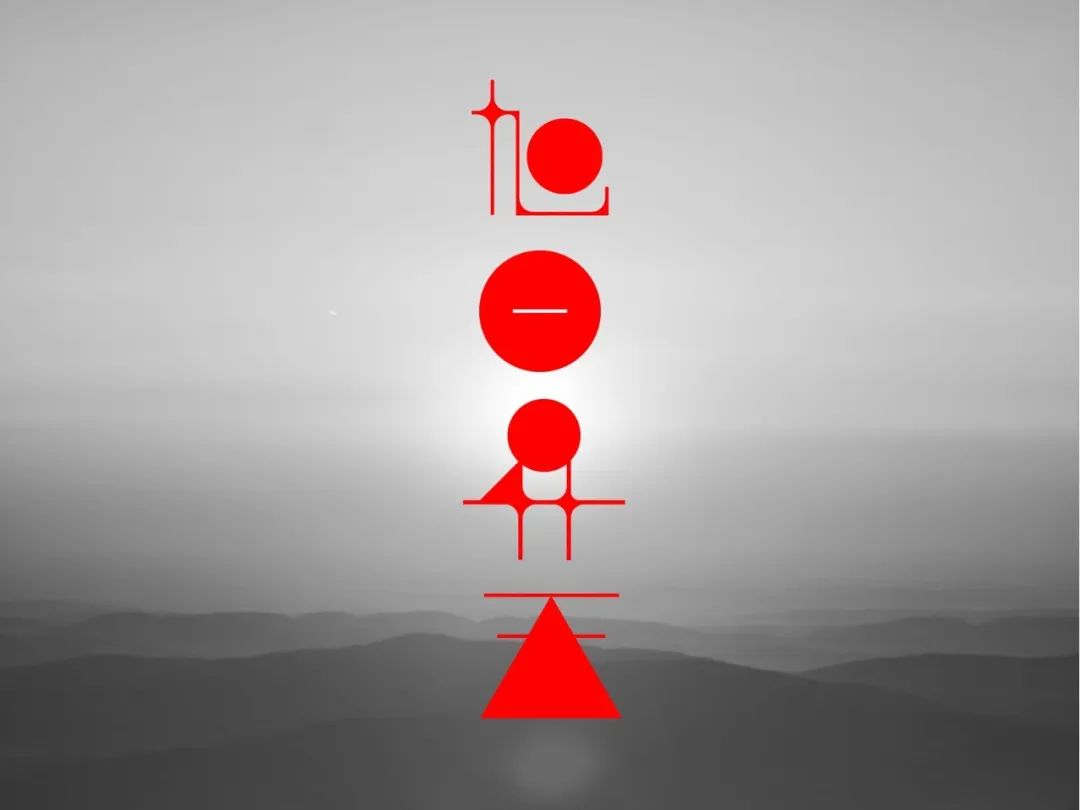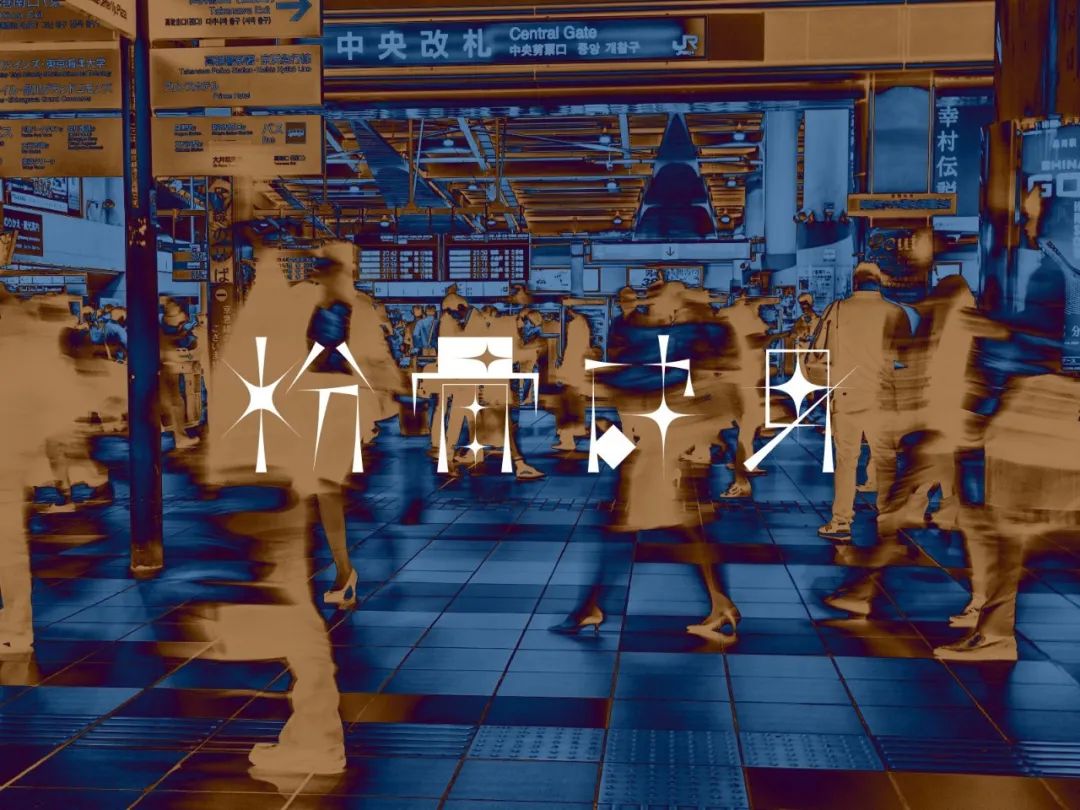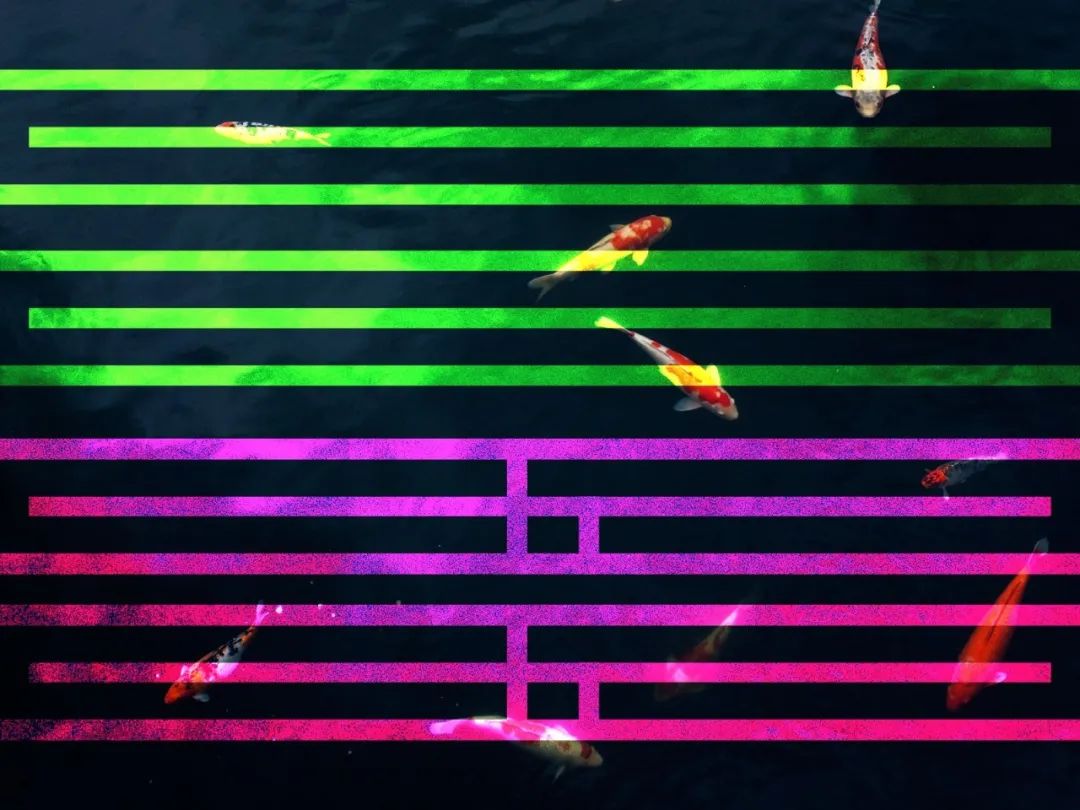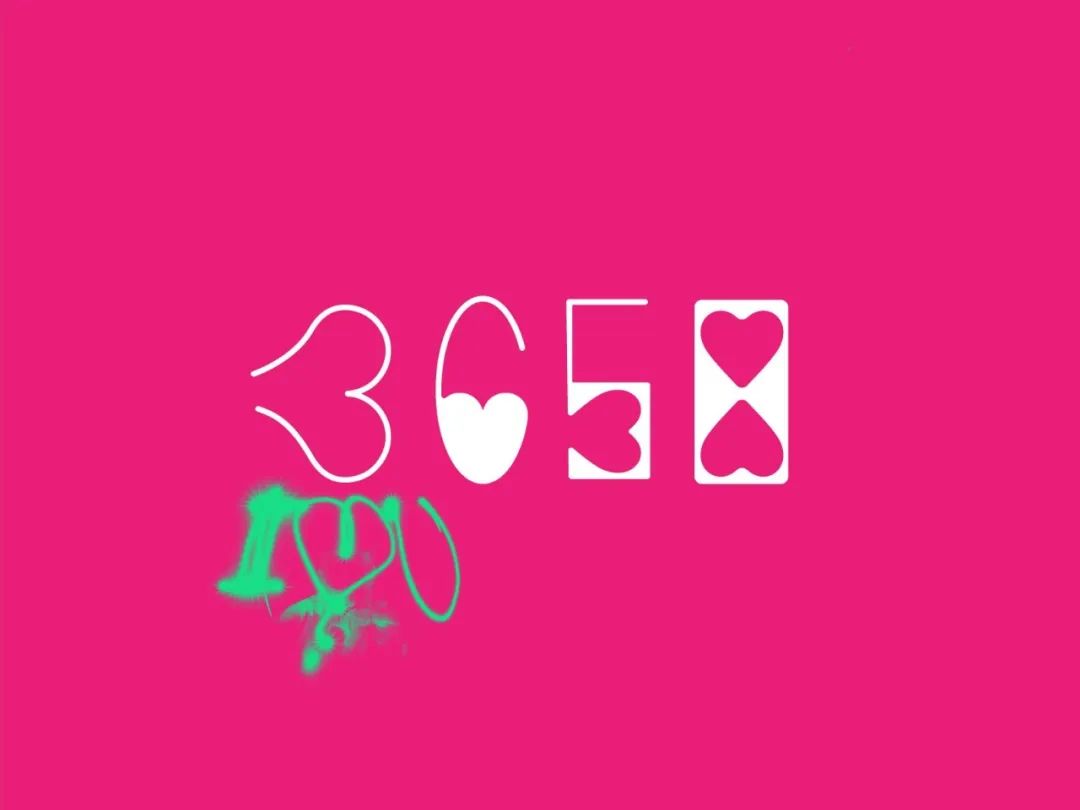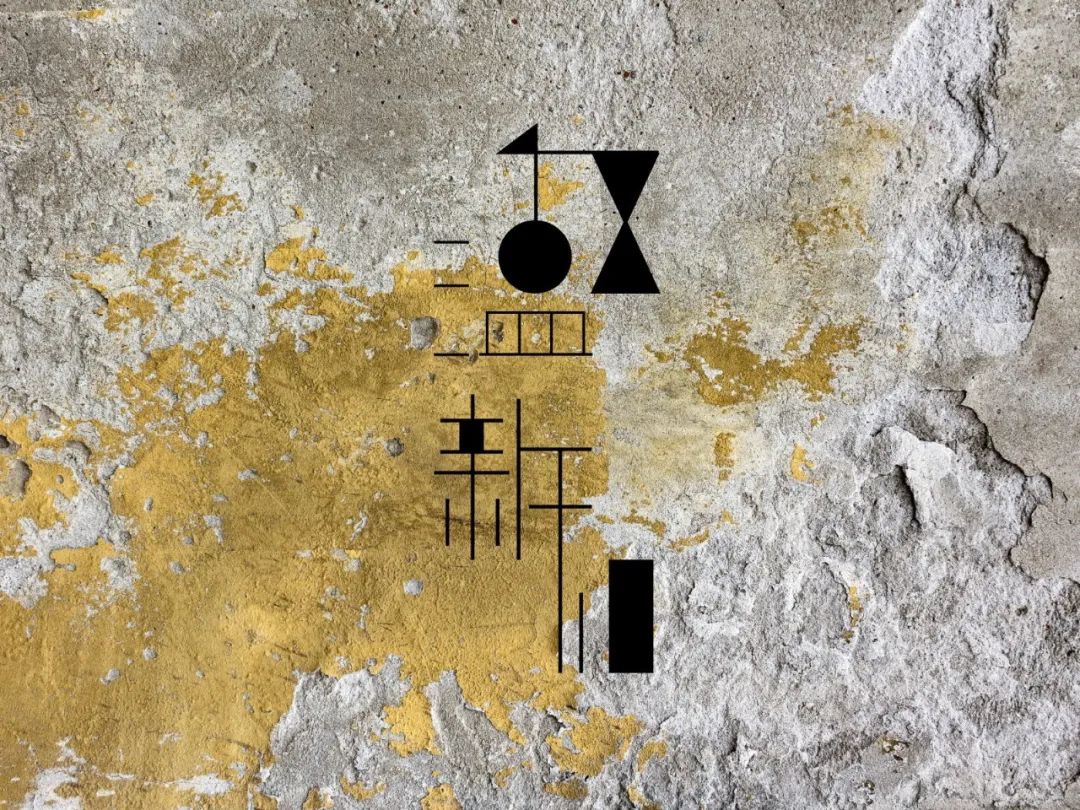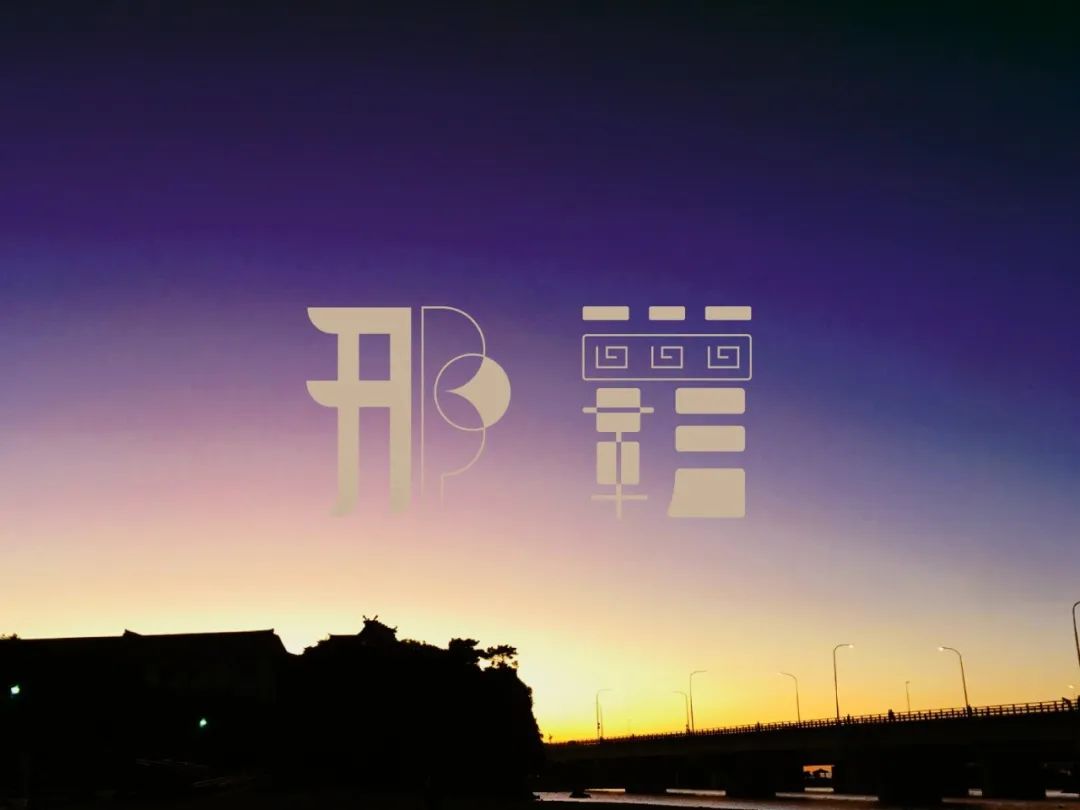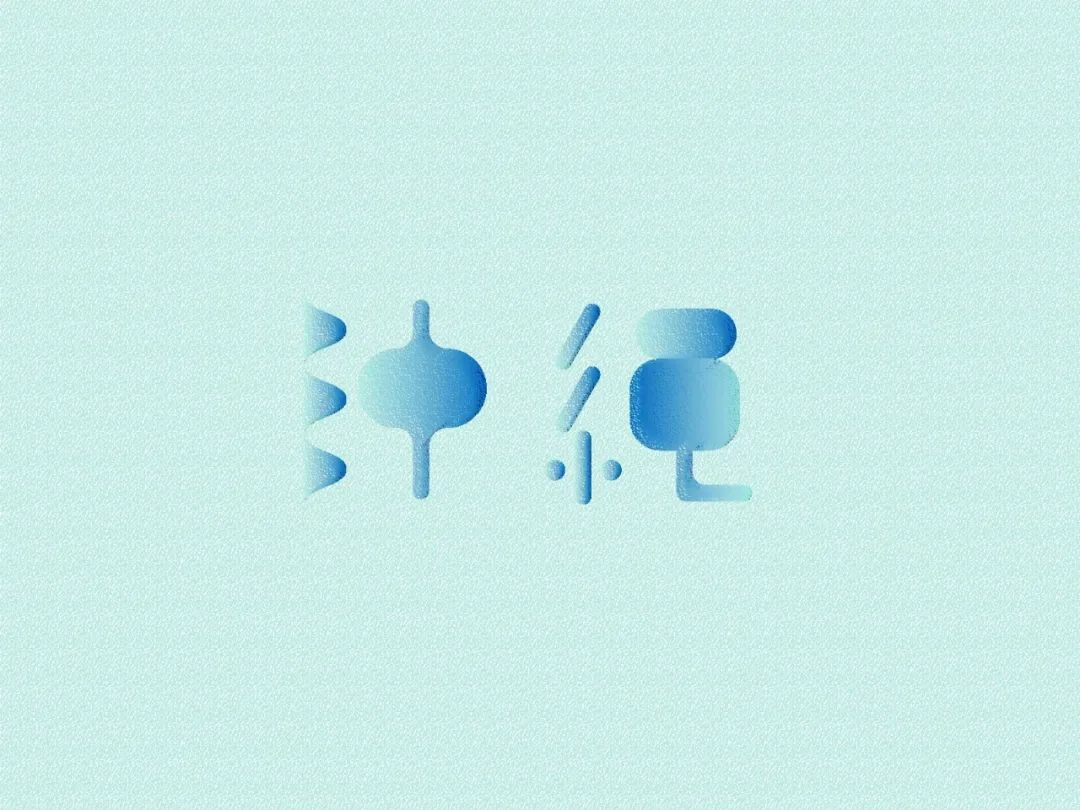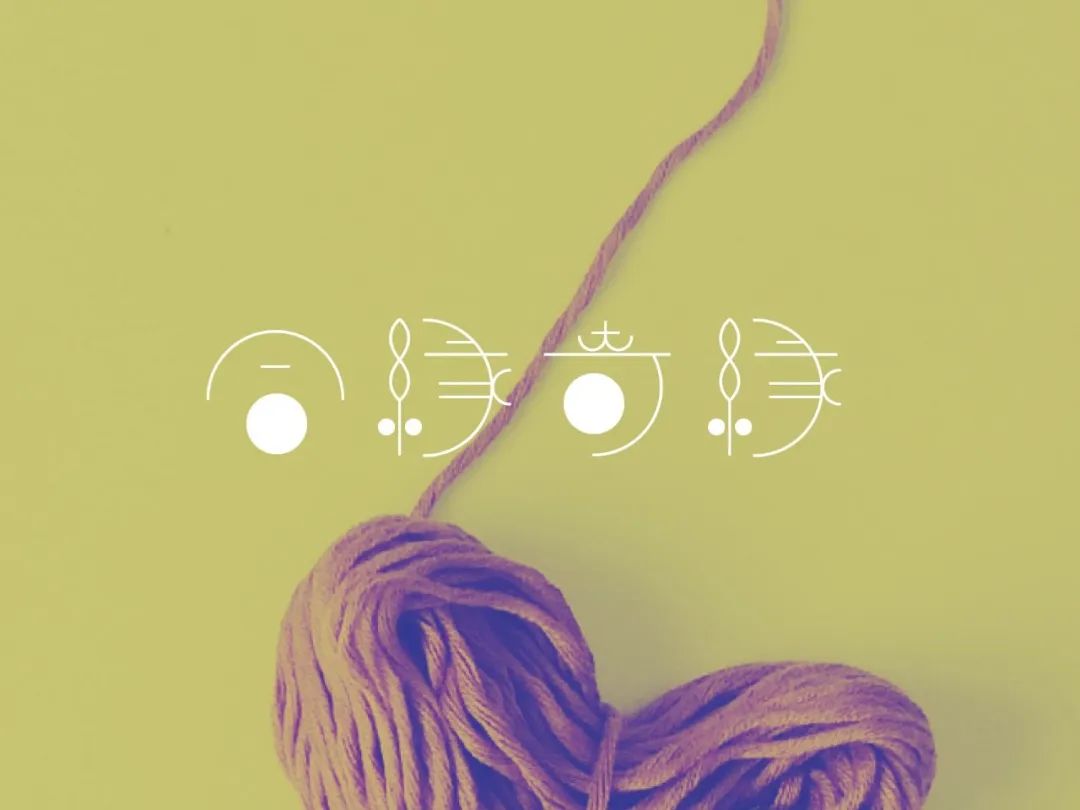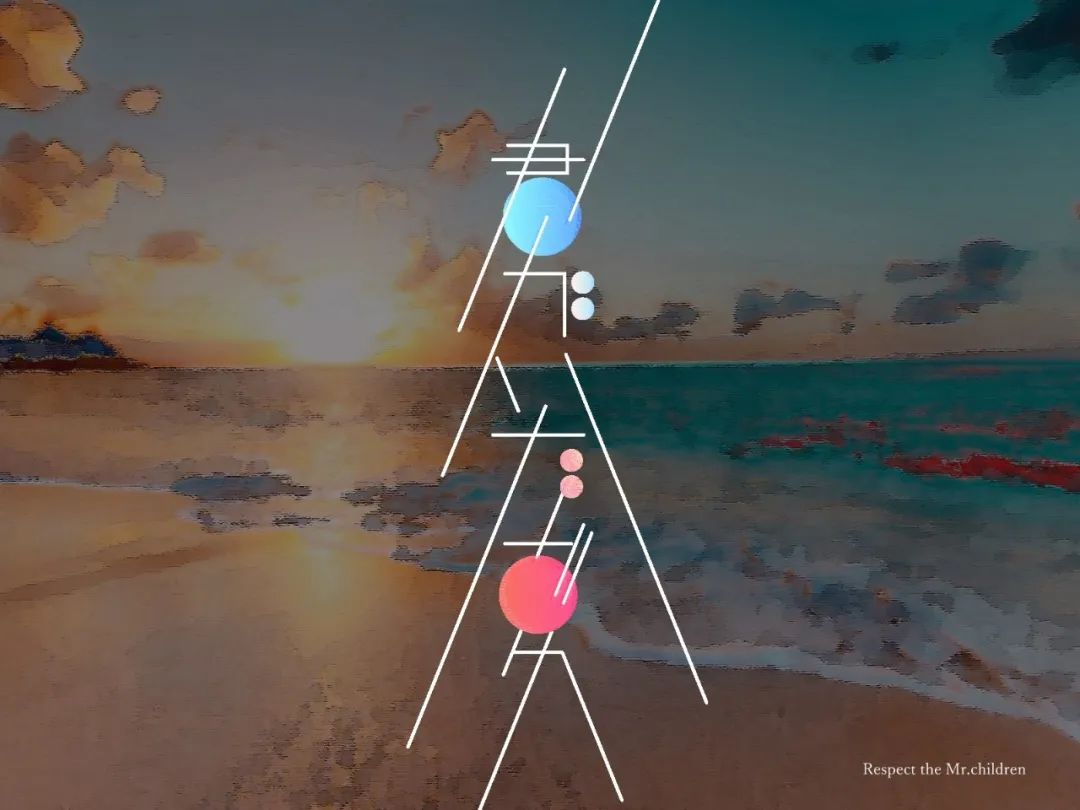
60张创意字体设计分享,带你感受冲出屏幕的生命力!
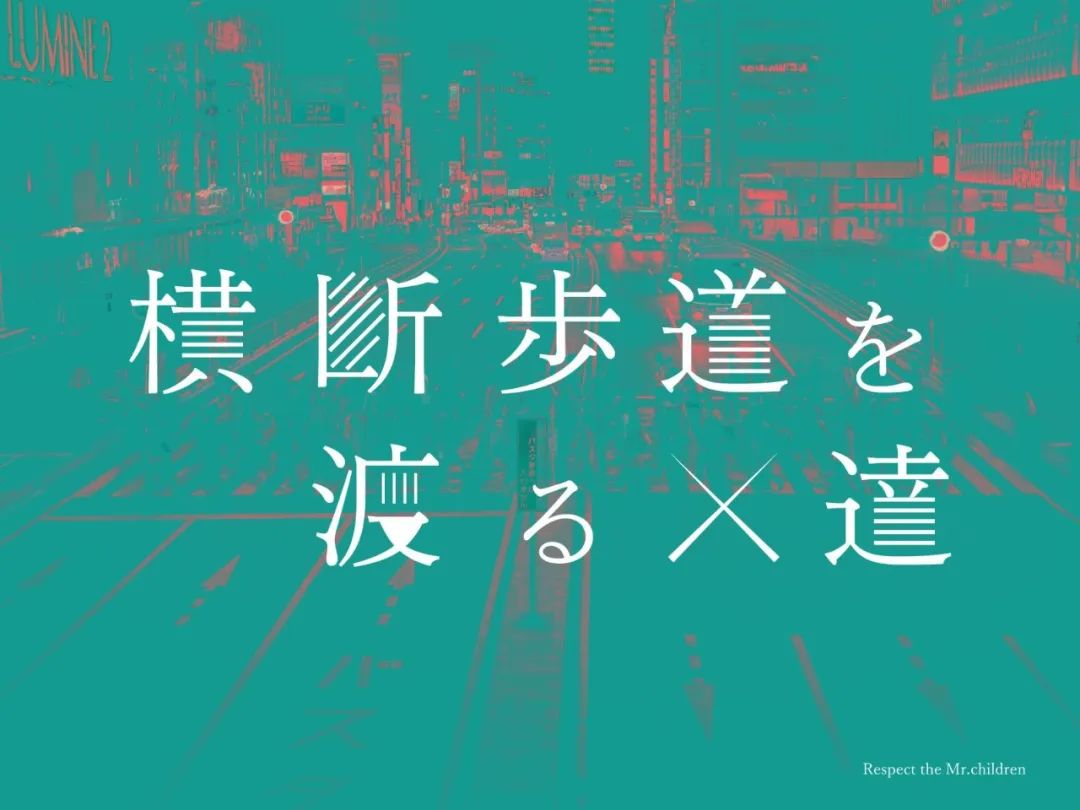
今天跟大家分享一位来自东京的平面设计师Mitsuru Terasaki 。他将文字与图形结合在一起,充满了生命力和感染力,看了他的作品,你还愁没灵感吗?
01
Mr.children 横断歩道を渡る人達
02
旭日昇天
03
粉骨砕身
04
三三五五
05
Mr.children 365日
06
温故知新
07
那覇(NAHA)
08
沖縄(OKINAWA)
09
合縁奇縁
10
Mr.children 君がいた夏
11
行雲流水
12
輪廻転生
13
海千山千
14
Mr.children 独り言
15
Mr.children 跳べ(Jump)
16
奇想天外
17
泡沫夢幻
18
侃侃諤諤
19
奔放自在
20
Mr.children 東京(Tokyo)
21
杓子定規(strict)
22
Mr.children 優しい歌
23
有耶無耶(obscure)
24
風林火山(Fu-Lin-Ka-Zan)
25
children 箱庭(Hakoniwa)
26
晴耕雨読
27
森羅万象(the universe)
28
小春日和(Indian summer)
29
落花流水(mutual love)
30
Mr.children 蜃気楼(a mirage)
31
掌(palm)
32
四角四面(a prim person)
33
疑心暗鬼
34
画竜点睛(finishing touch)
35
Mr.children 声(Voice)
36
一期一会
37
自業自得
38
品行方正(Well-behaved)
39
Mr.children 傘の下の君に告ぐ
40
発見(Discovery)
41
Mr.children 天頂バス
42
Mr.children あんまり覚えてないや
43
Mr.children 幻聴
44
Mr.children 潜水
45
Mr.children 星になれたら
46
Mr.children 花言葉(flower language)
47
Mr.Children 常套句
48
Mr.children 斜陽
49
Mr.children 祈り
50
Mr.children やわらかい風
51
Mr.children 通り雨
52
Mr.children 虜
53
Mr.children 箒星
54
Mr.children 花
55
Mr.children 靴ひも
56
Mr.children 隔たり
57
Mr.children 君が好き
58
Mr.children 渇いたKiss
59
Mr.children 雨のち晴れ
60
Mr.children 深海
在现代平面设计中,文字要传达的不仅仅是信息,还要给人耳目一新的冲击力。如韩国设计师Jaemin Lee 所说:“关于平面设计,最终的意象需要传达的是模糊还是明确的信息,取决于字形是如何被视觉化的。作为一种沟通的媒介,我相信字体有着其它图形元素所没有的独特魅力。”